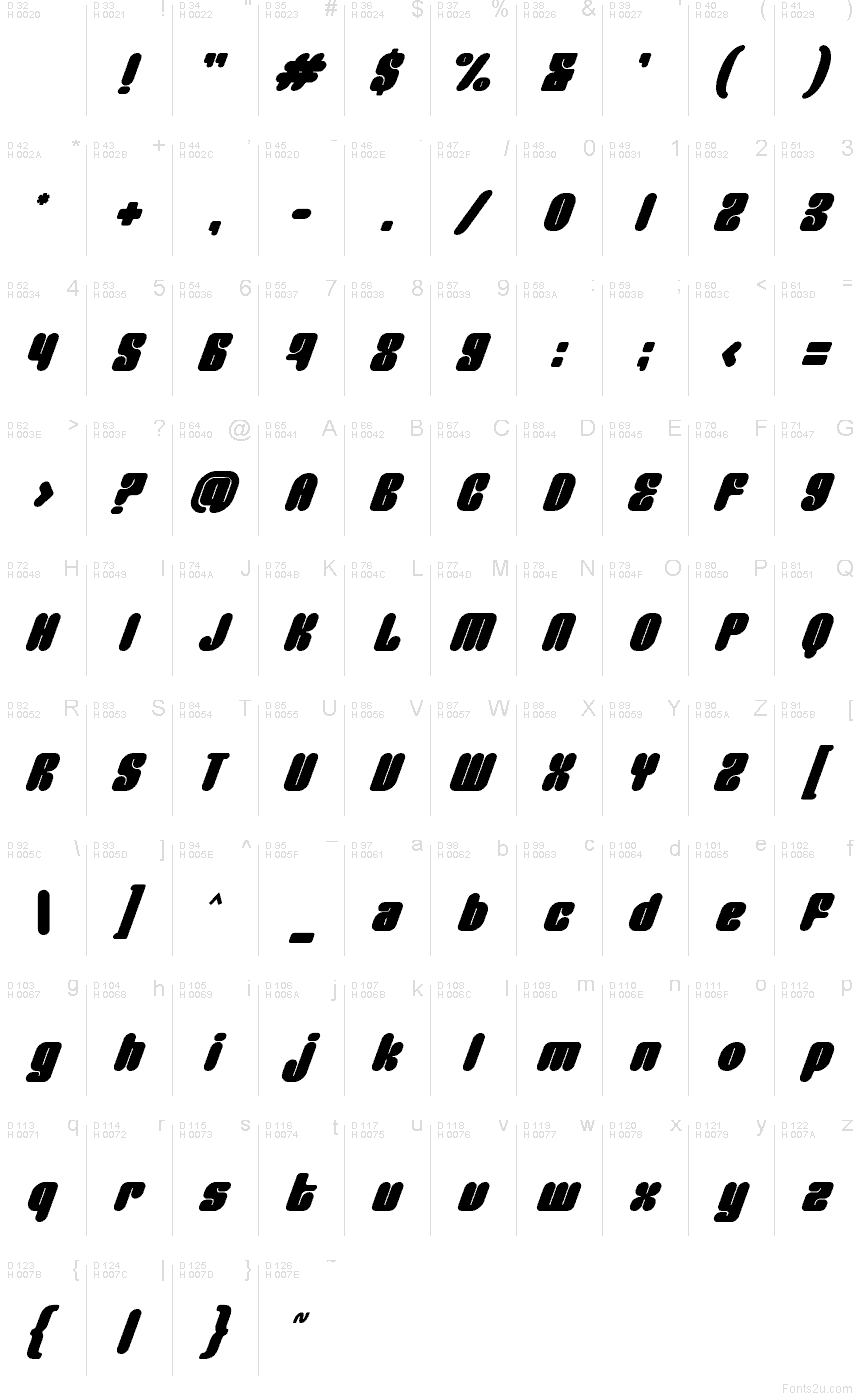
Dynamic Display Six od Putracetol Studio je bezplatné zaoblené display písmo definované tupými, šikmými siluetami, které připomínají měkké černé kapsle proříznuté úzkými vnitřními štěrbinami. Toto opakující se naklonění dodává písmu rychlý, zhuštěný rytmus, zatímco uzavřené tvary udržují celkovou texturu hustou a grafickou, namísto vzdušné.
Plakáty, hudební grafika, streetwear branding, herní tituly a bannery na sociálních sítích mohou využít tuto kompaktní hmotu k tomu, aby krátká slova působila bezprostředně. Dynamic Display Six se také hodí pro obalový design a experimenty s logy, kde úhlové formy a vyříznuté otvory dodávají textu drsný, stylizovaný náboj, aniž by potřebovaly další zdobení.